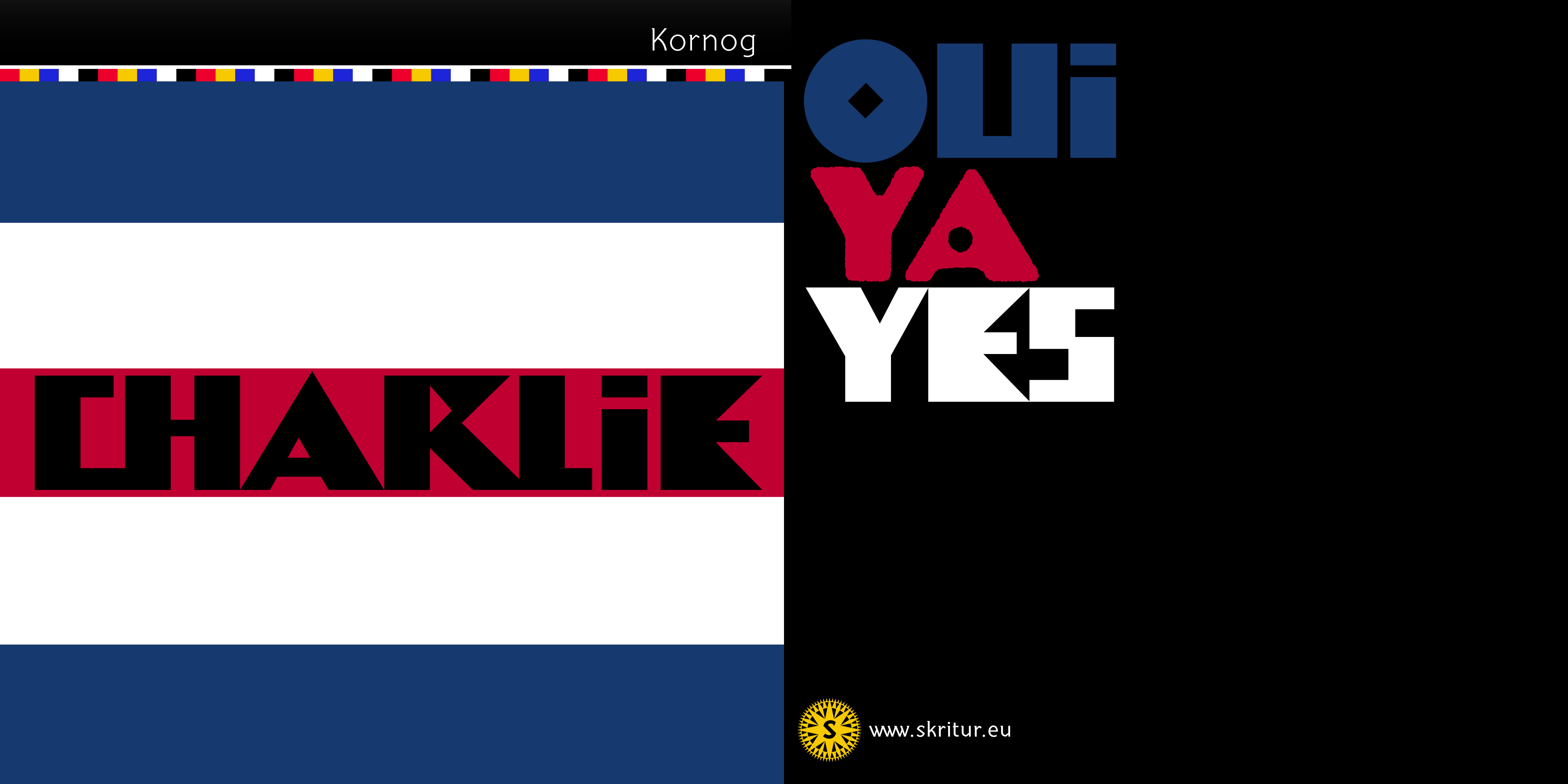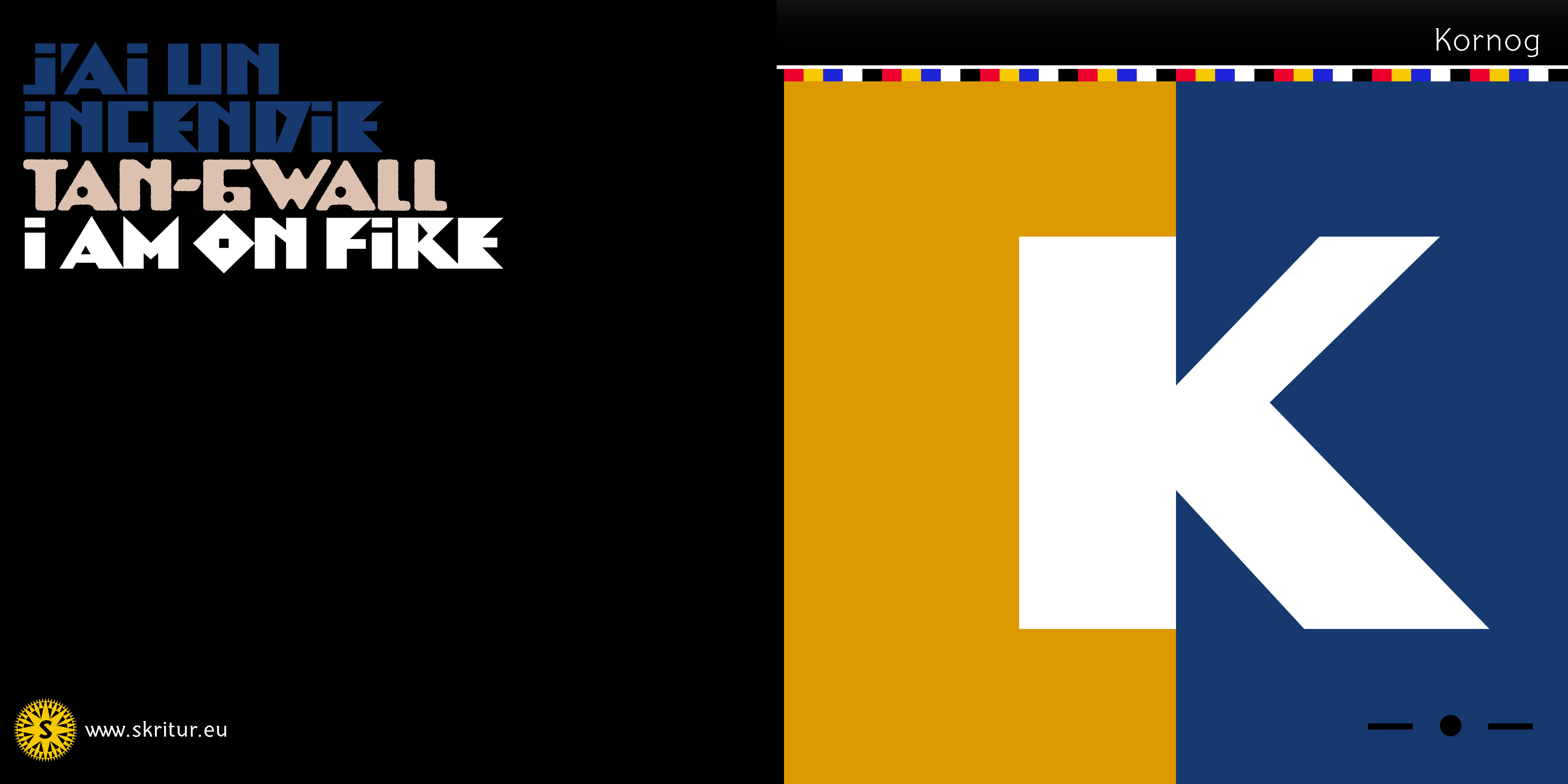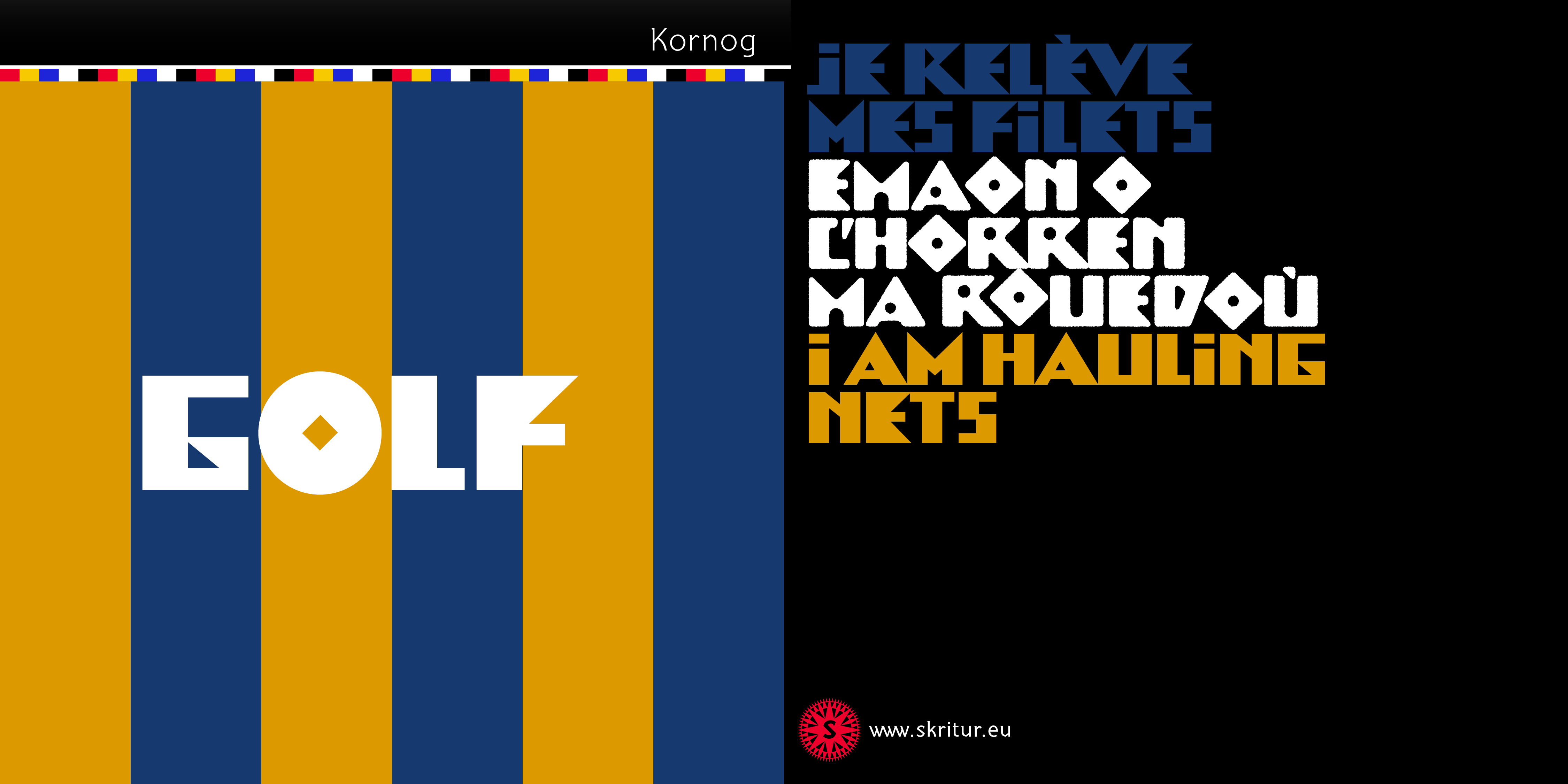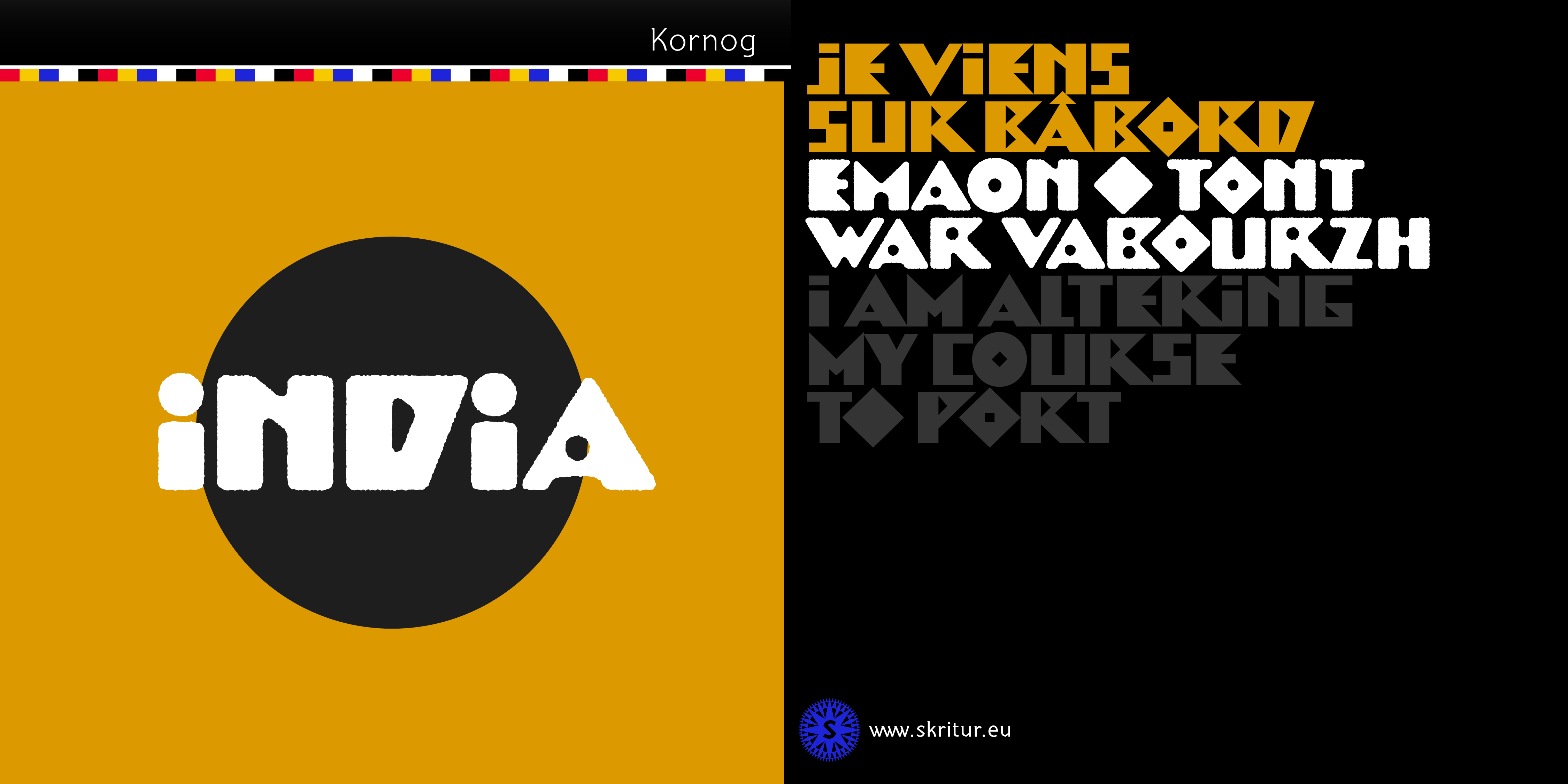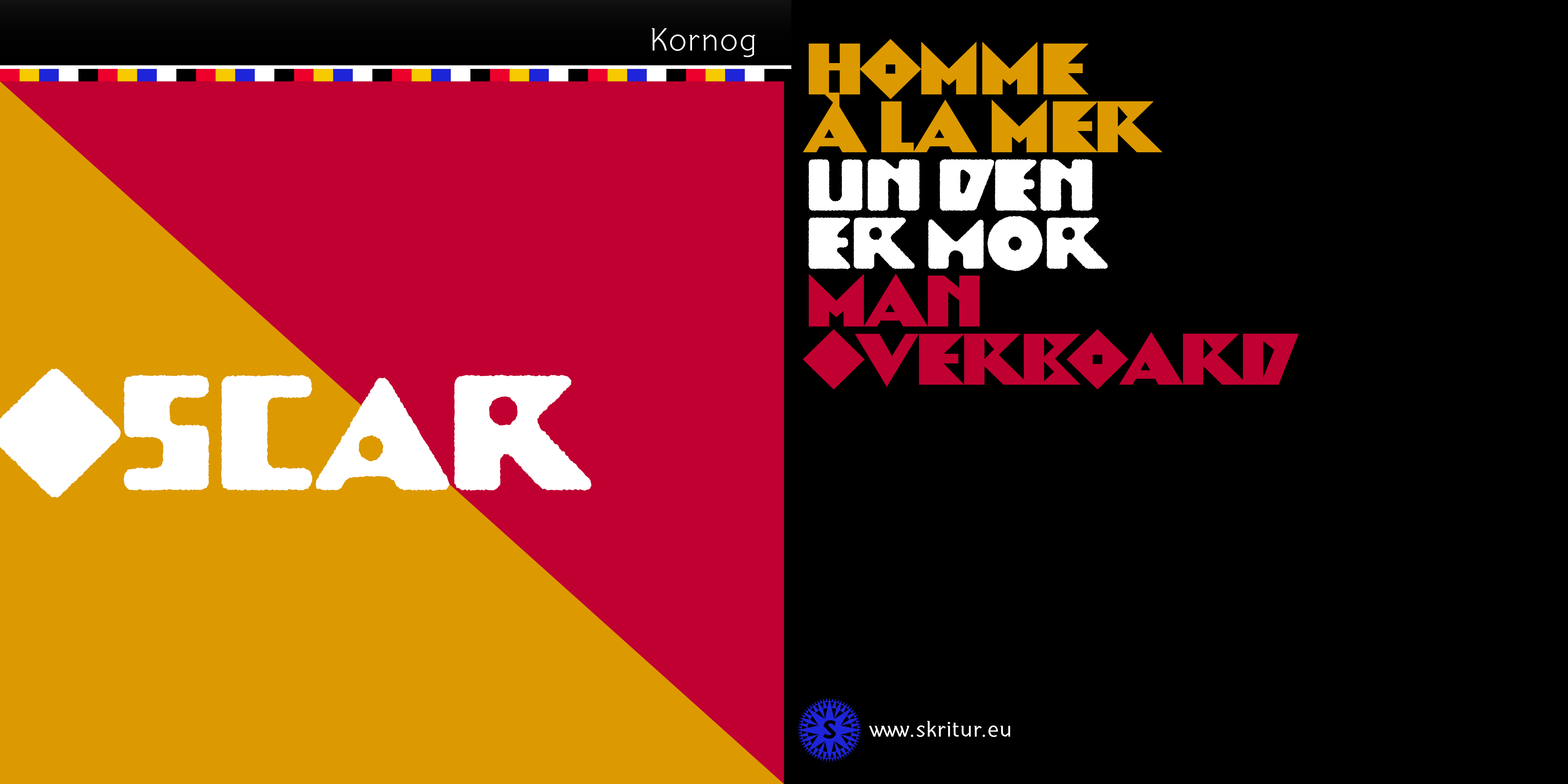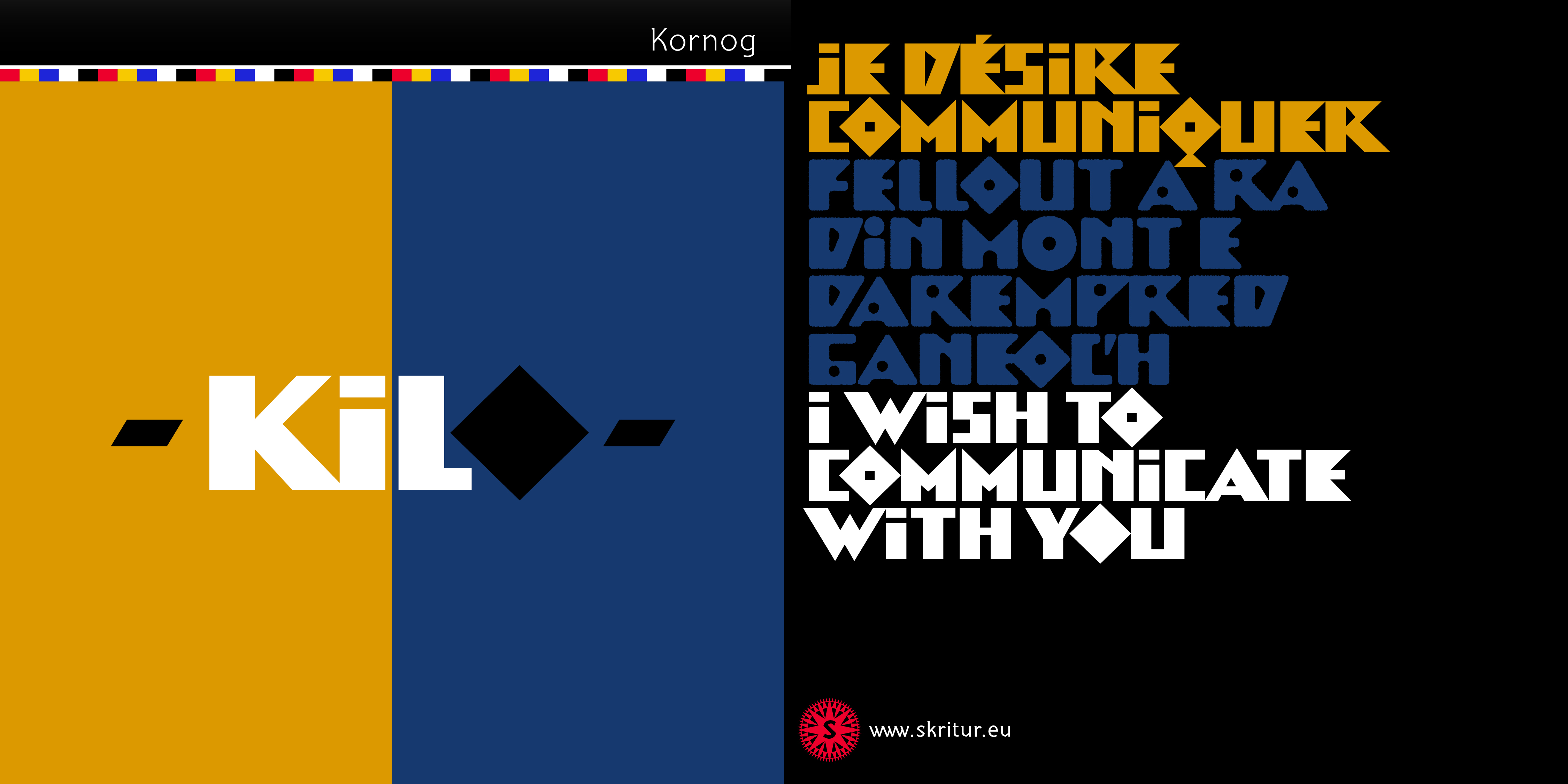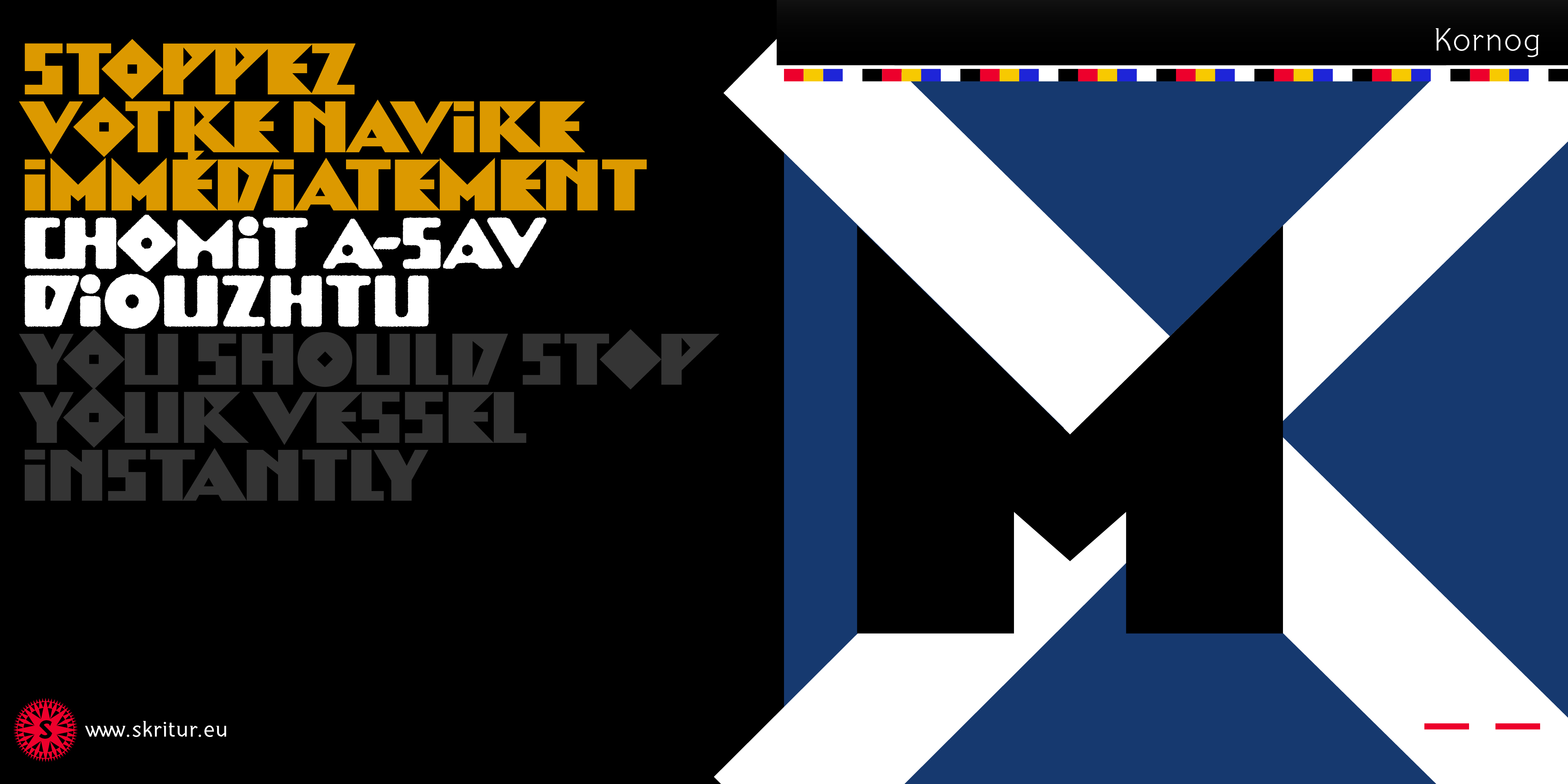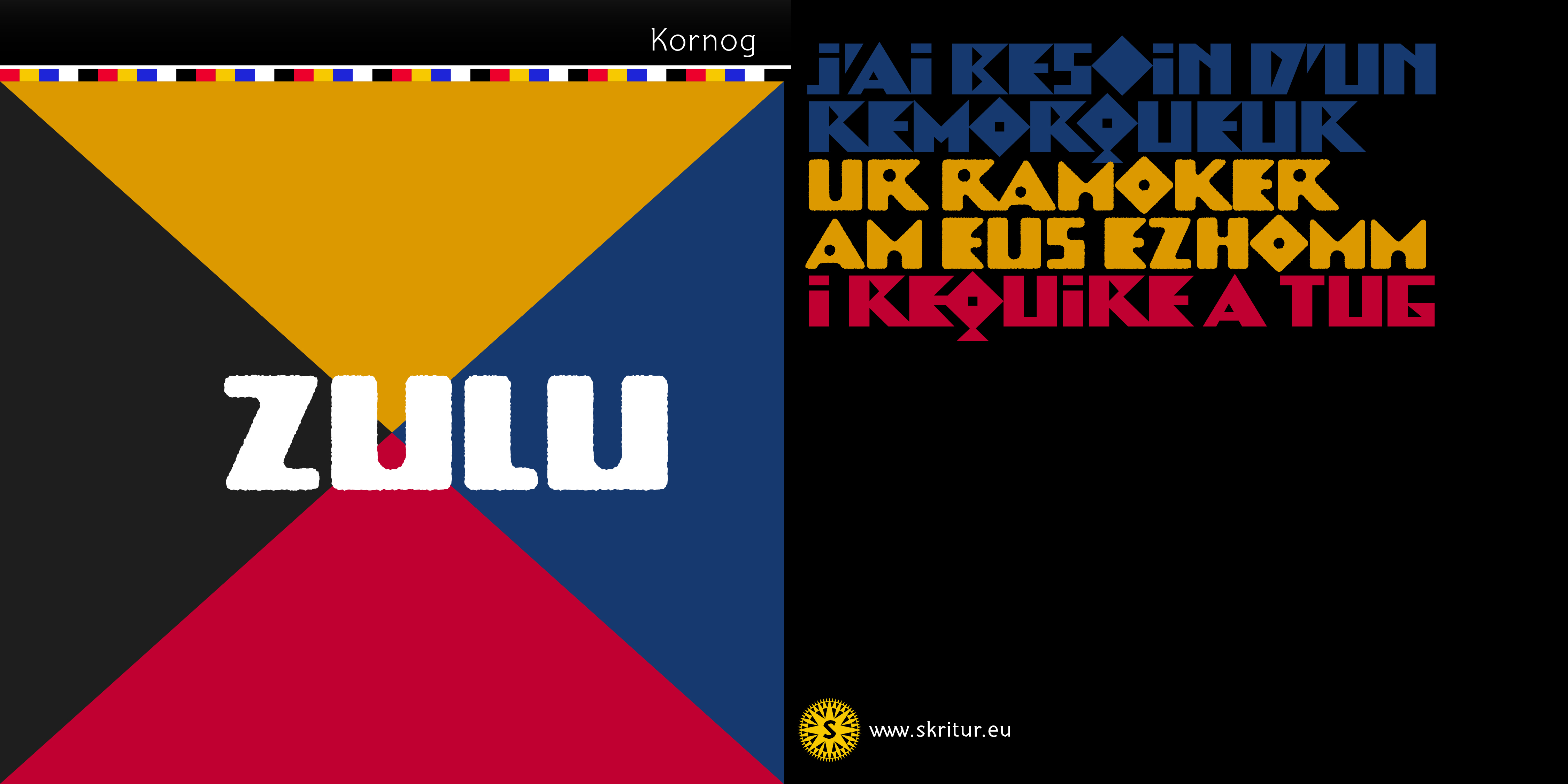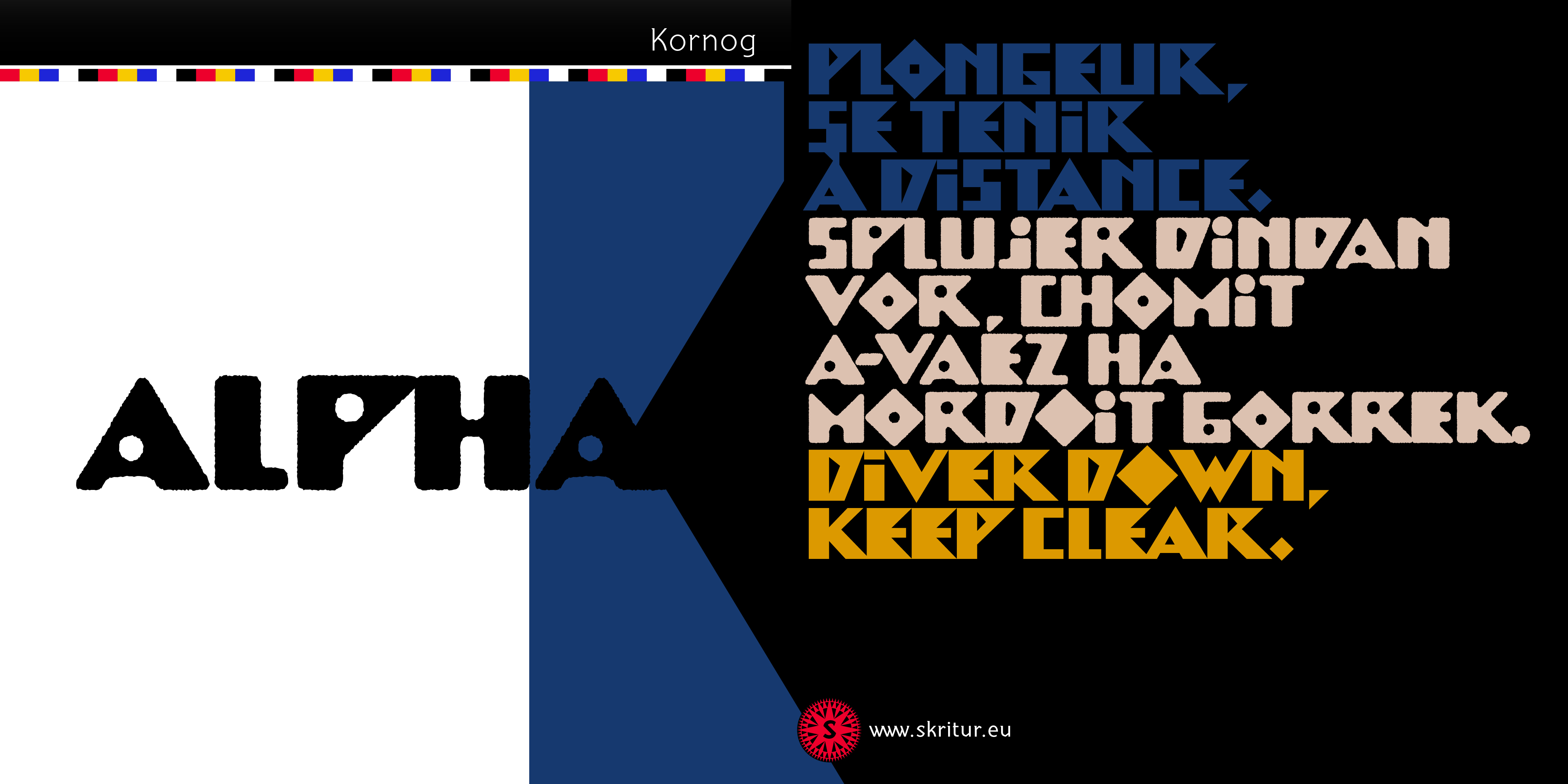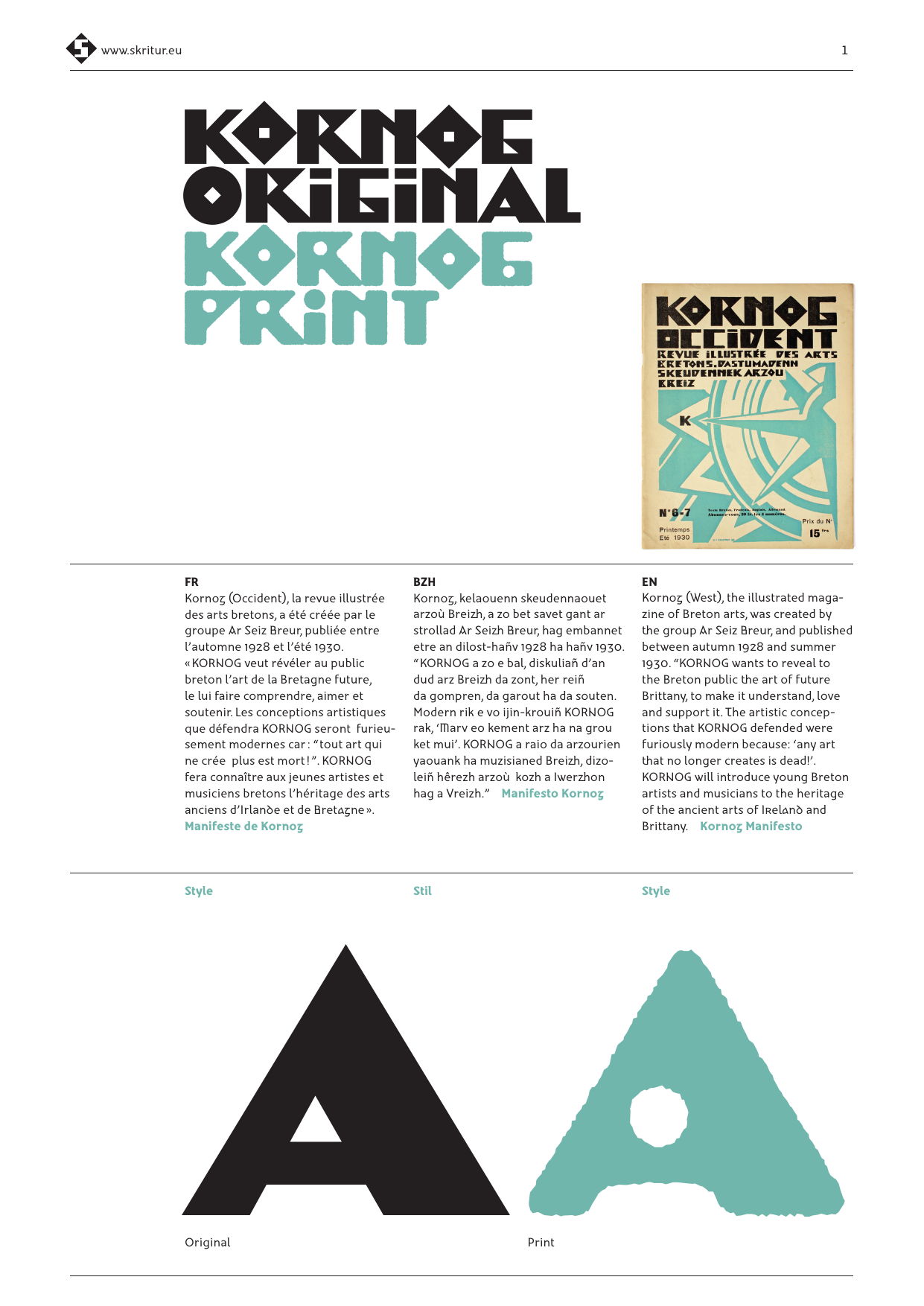
Kornog
KORNOG (Occident)
Créée en 1928 par le groupe Ar Seiz Breur, la revue KORNOG devient rapidement la référence du renouveau artistique en Bretagne au début du XXe siècle.
En 1995, lors de la publication de son ouvrage Skritur – typographie & identité, le graphiste Fañch Le Henaff présentait un premier alphabet dessiné à partir de la têtière de la revue, gravée sur bois par René-Yves Creston et Suzanne Candré-Creston, tous deux cofondateurs du collectif, avec Jeanne Malivel et Jorj Robin. Pour célébrer le centenaire du mouvement, le caractère Kornog est aujourd’hui revu et augmenté afin d’en permettre un usage pour le titrage (presse, affiche, édition…) qui n’a rien à envier à la radicalité formelle prônée par ces artistes de l’Art déco breton : géométrique, acéré et puissant. Une version «print» donne au Kornog une saveur rétro où l’on assume les imperfections de l’impression des caractères bois et l’encrage fluctuant d’un tirage à l’autre.
KORNOG
Krouet e 1928 gant ar strollad Ar Seizh Breur, ar gelaouenn KORNOG a zo deuet da vezañ buan, arouezenn dave arzel Breizh e derou an XXvet kantved.
E 1995, p’eo bet embannet e levr “Skritur -tipografiezh hag Identelezh”, ar grafour Fañch an Henaff a ginnige e lizherenneg gentañ treset, hervez golo ar gelaouenn, engravet war goad gant René-Yves Kreston ha Suzanne Candré-Kreston, kengrouerien o daou ar strollad gant Jeanne Malivel ha Jorj Robin. Evit lidañ kant vloaz al luskad, eo bet adkrouet an arouezenn Kornog, hag ouzhpennet evit un implij evit an titloù (kazetennoù, skritelloù embannadurioù) gant stummoù krenn kinniget gant arzourien an Arz-deko breizhek : mentoniel, dirennet ha kreñv. Ur stumm “moullet” o reiñ da Gornog un doare a c'hiz kozh gant diglokterioù moullañ an arouezennoù koad o cheñchañ eus an eil moulladenn d’eben.
KORNOG (West)
Created in 1928 by the group Ar Seiz Breur, the magazine KORNOG quickly became the reference for artistic renewal in Brittany at the beginning of the 20th century. In 1995, when Skritur – typographie & identité was published, the graphic designer Fañch Le Henaff presented a first alphabet drawn from the masthead of the magazine, engraved on wood by René-Yves Creston and Suzanne Candré-Creston, both co-founders of the collective, with Jeanne Malivel and Jorj Robin. To celebrate the movement’s centenary, the Kornog typeface has now been revised and enhanced so that it’s suitable for titling (press, poster, publishing, etc.) in a way that is in keeping with the formal radicalism advocated by these Breton Art Deco artists: geometric, sharp and powerful. A “print” version gives Kornog a retro flavour, where the imperfections of the wooden characters and the fluctuating inking from one print run to the next are fully assumed.